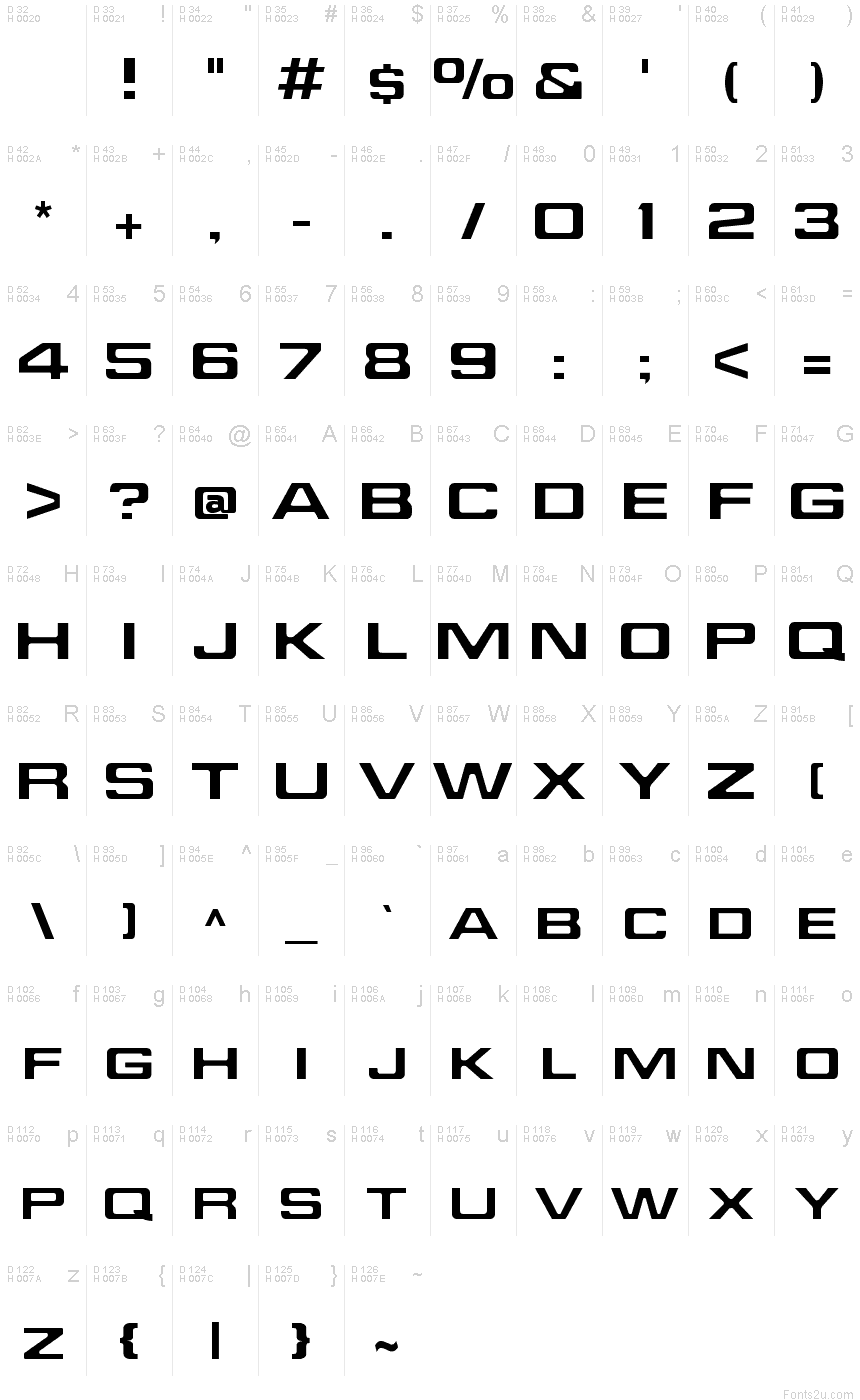
Anteprima del carattere Jefferies Extended
Il font Jefferies Extended di Jeff Yerkey è un carattere display techno gratuito. Le sue forme ampie e squadrate, con gli angoli tagliati, sembrano stampate sulla scocca di un'astronave: rigide, sicure e innegabilmente futuristiche. L'ampiezza estesa conferisce a ogni parola una presenza scenica, facendo sì che i titoli si distendano sulla pagina con un ritmo meccanico costante.
Con Jefferies Extended puoi dare un tono audace e ingegneristico a poster sci-fi, mockup di interfacce, titoli di giochi, branding tecnologico, badge per eventi e overlay per streaming. Questo font gratuito risalta nei grandi formati, dove la sua geometria massiccia può respirare; abbinalo a un semplice carattere sans serif per il testo principale e le etichette per garantire leggibilità, mantenendo il layout saldamente ancorato al futuro.
Designed by Jeff Yerkey (www.trek5.com) in honor of Matt Jefferies and Michael Okuda.